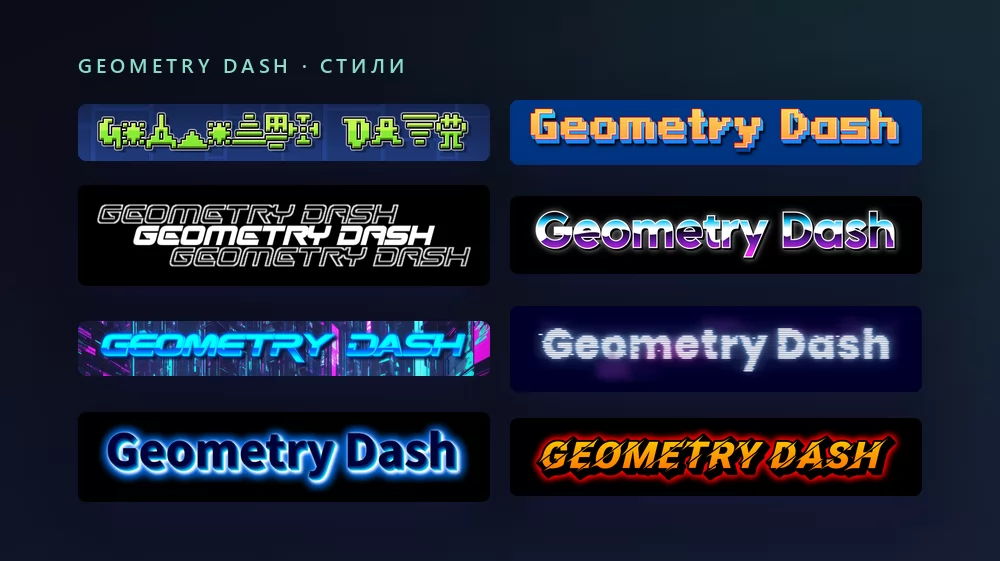
О шрифте Geometry Dash
Geometry Dash это ритмический платформер, вышедший в 2013 году на iOS и Android, а затем в Steam, созданный шведским разработчиком Робертом Топалой и изданный его компанией RobTop Games. Вы тапаете, чтобы кубик перепрыгивал шипы в такт музыке, одно касание и всё сначала, а редактор уровней превратил игру в мир с миллионами пользовательских уровней и целой сценой на YouTube.
Работу делают два шрифта, и «шрифт Geometry Dash» может означать любой из них. Логотип набран шрифтом Oxygene 1, пиксельным шрифтом Якоба Фишера, дизайнера, стоящего за Pizzadude. Текст внутри игры, названия уровней, меню, логотип RobTop, очень близок к Pusab, толстому округлому шрифту студии Flat-it. Игроки, говорящие «шрифт GD», обычно имеют в виду второй, потому что видят его на каждом уровне.
Как сделать текст в стиле Geometry Dash
Шаг 1. Введите слово
Откройте генератор и замените пример своим текстом: название уровня, название канала, заголовок видео, ваш ник. Буквы перерисовываются прямо во время набора.
Шаг 2. Выберите стиль
Стиль целевой страницы собирает каждую букву из иконок уровней на синей сетке редактора. Это самое «Geometry Dash» в списке, и его труднее всего читать в мелком размере, так что для ника или превью переключитесь на пиксельный стиль, совпадающий с логотипом. На вкладке «Стили» заливка, обводка и тень меняются отдельно в обоих.
Шаг 3. Выберите формат
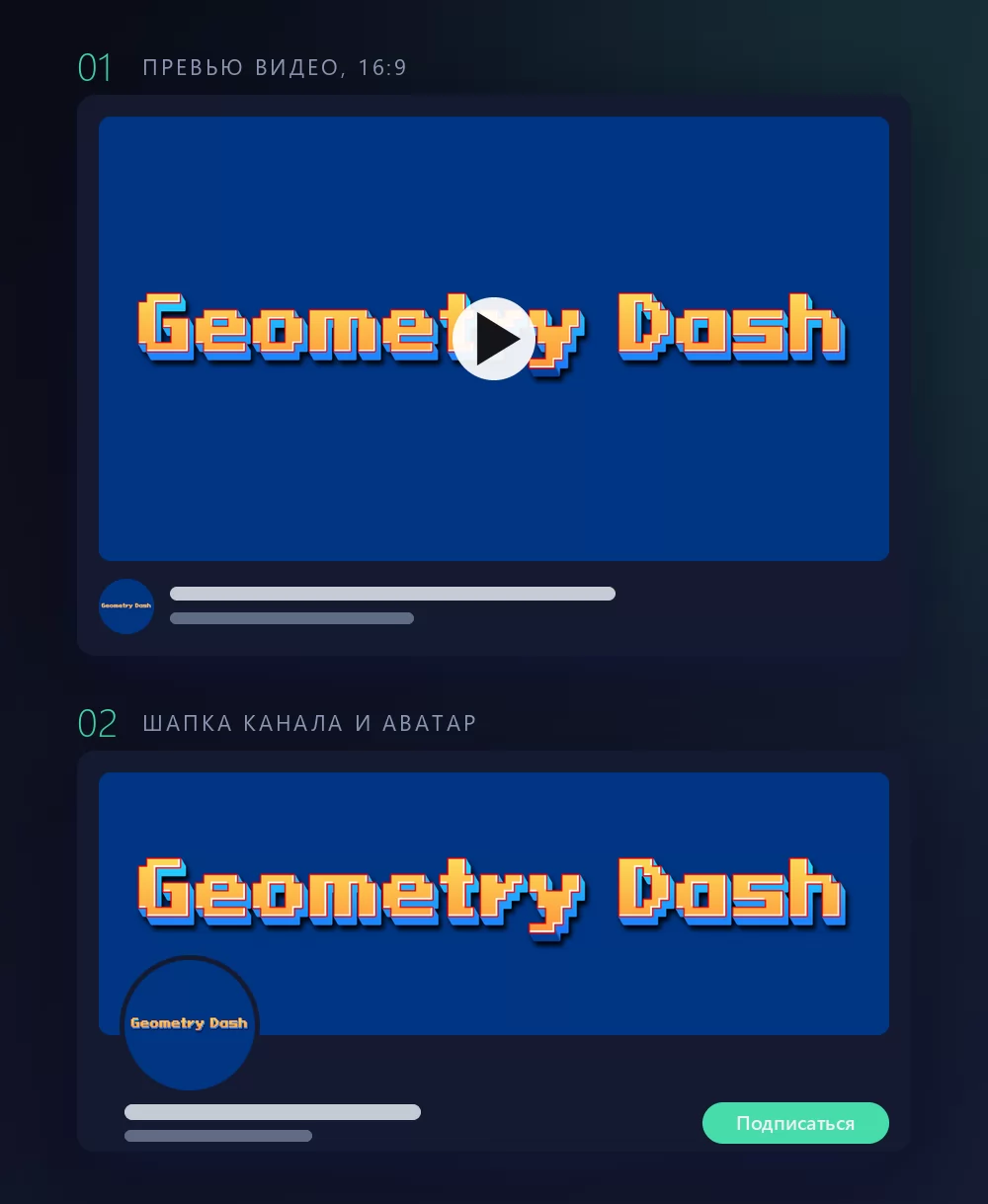
Задайте формат до экспорта, и потом ничего обрезать не придётся. 16:9 для превью видео, квадрат для аватара или иконки в Discord, широкая полоса для шапки канала. Два макета выше показывают, во что превращаются эти три формата на своём месте.
Шаг 4. Скачайте
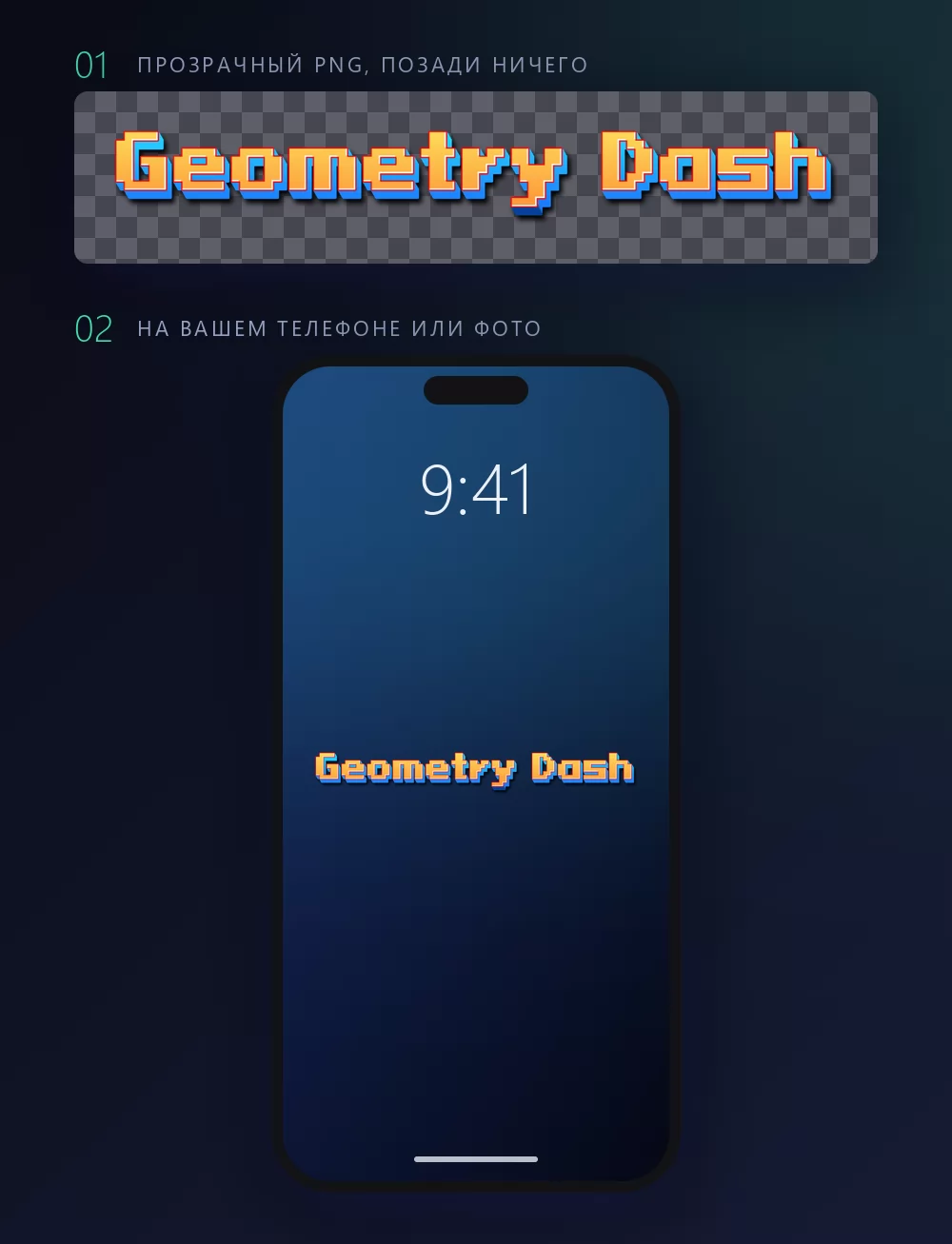
На вкладке «Скачать» берите прозрачный PNG, если собираетесь положить название на свой скриншот. Эту опцию большинство пропускает, а для превью уровня именно она и важна: ваш скриншот уровня позади, название сверху, никакой синей рамки вокруг.
Длинные имена быстро заполняют ширину
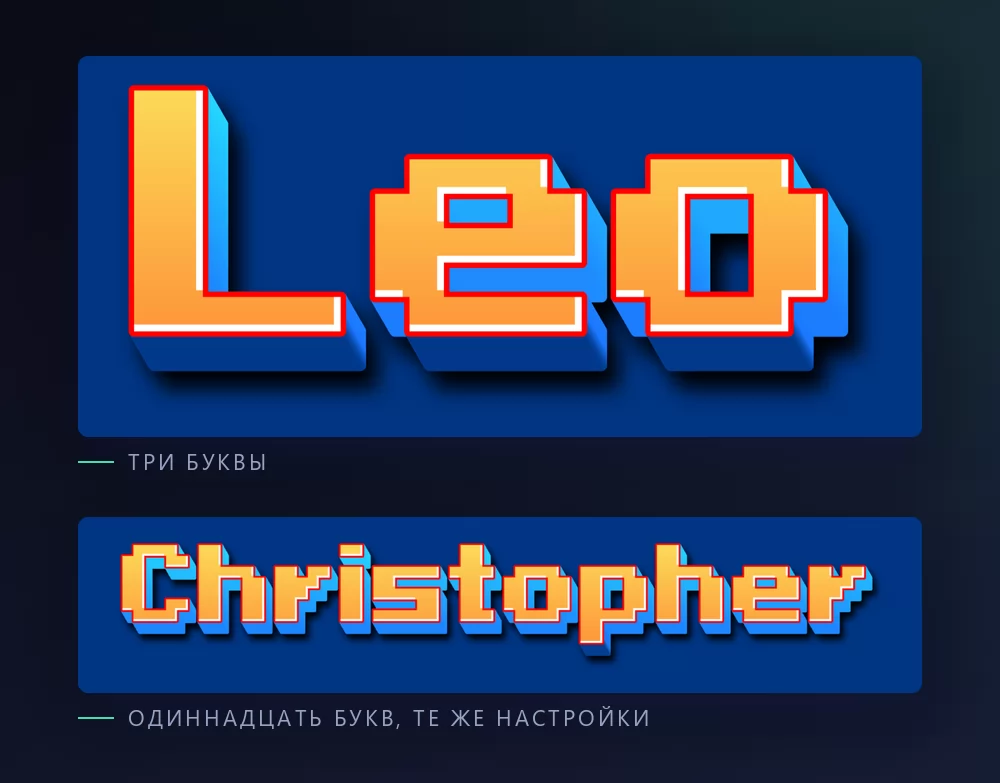
Чем больше букв, тем плотнее они сидят. Межбуквенный интервал это ползунок на вкладке «Текст»: чуть раздвиньте, и длинное имя перестанет выглядеть сжатым. На той же вкладке масштаб, межстрочный интервал, изгиб и поворот.
Стиль логотипа или стиль уровней
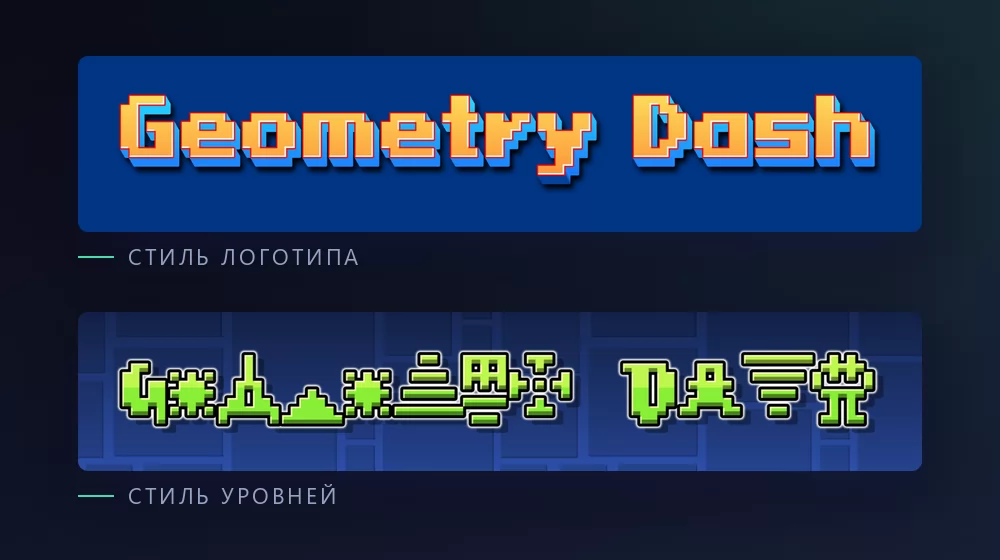
Стиль логотипа это пиксельная надпись, Oxygene 1 с титульного экрана: квадратные буквы с тёмной обводкой, оранжевые на синем. Он читается в любом размере, поэтому именно он нужен для ника.
Стиль уровней это сам текстовый эффект Geometry Dash: каждая буква собрана из кубов, шипов и порталов на сетке редактора. Он с первого взгляда говорит об игре, и его место на превью, а не на аватаре, который сожмут в кружок.
Какой шрифт, если вы хотите его установить
Ради вида Pusab с чистой лицензией честные варианты это толстые округлые шрифты на Google Fonts: Luckiest Guy, ближайший по насыщенности и упругости, Bowlby One Вернона Адамса, тяжелее, и Titan One Родриго Фуэнсалиды, чуть уже. Все три под открытой лицензией, все три доступны в Canva, и ни один из них не Pusab. Они дают силуэт, а в размере превью это почти всё, что читает глаз.
Что с ним делают на самом деле
Прежде всего превью уровней для YouTube: название уровня игровыми буквами поверх скриншота самого сложного места. Затем баннеры каналов, аватары Discord и YouTube, карточки профиля на сайтах сообщества, обои на телефон и изредка напечатанная футболка для встречи. Почти всё это лучше работает с прозрачным PNG, чем с установленным шрифтом, потому что вид это обводка и тень не меньше, чем буквы, а файл шрифта даёт только контуры.
Как сделать текст Geometry Dash в Canva
В Canva нет ни Pusab, ни Oxygene 1. Зато есть Luckiest Guy, Bowlby One и Titan One, так что толстый вид можно получить, не выходя из неё. Ради пиксельного логотипа или стиля уровней сделайте надпись прозрачным PNG и загрузите её: она сразу встанет в превью Canva и останется чёткой.
Как сделать текст Geometry Dash в Photoshop
Установите Oxygene 1 для стиля логотипа или Luckiest Guy для стиля игры, наберите текст и соберите оформление стилями слоя:
Почему мой пиксельный текст размытый? Сглаживание или масштаб, не кратный целому числу. Отключите сглаживание, держите шрифт в размере, кратном его пиксельной сетке, и экспортируйте в финальном размере, а не масштабируйте потом.